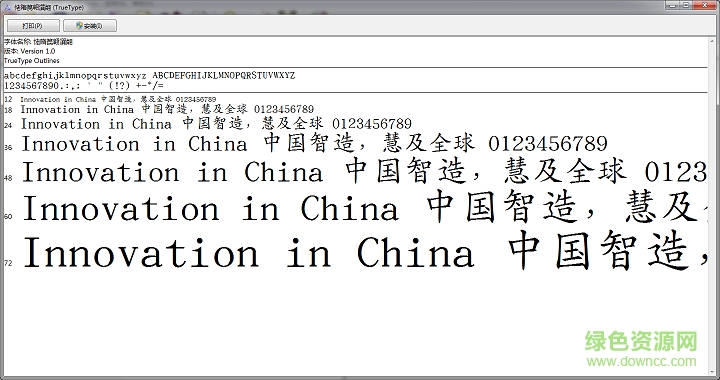
gbzenkai medium(文鼎中楷簡(jiǎn))字體是一款楷書字體,該字體棱角分明,氣質(zhì)幽雅,美觀而不落俗套,可以用于平面設(shè)計(jì)、廣告設(shè)計(jì)等方面!
楷書也叫正楷、真書、正書。由隸書逐漸演變而來(lái),更趨簡(jiǎn)化,橫平豎直?!掇o?!方忉屨f它“形體方正,筆畫平直,可作楷?!?。這種漢字字體端正,就是現(xiàn)在通行的漢字手寫正體字。
1~3厘米的為小楷(小字),
5厘米以上的為大楷(大字),
之間的為中楷。